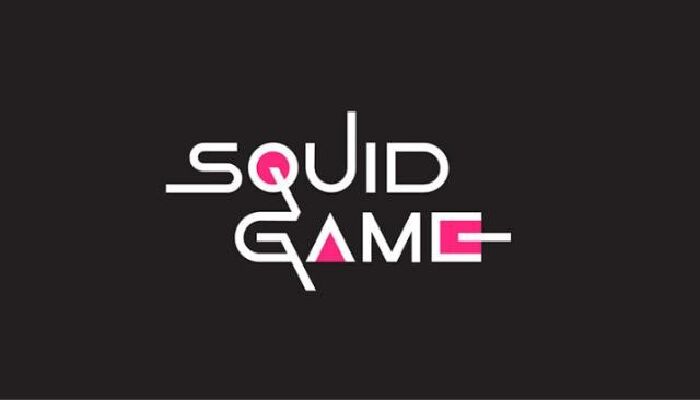
Nếu đã từng coi hoặc biết đến squid game ( trò chơi con mực) thì hẳn là bạn sẽ không còn xa lạ với những kiểu chữ phá cách khác biệt với kiểu chữ truyền thống theo một tiêu chuẩn
Những chữ cái thuộc kiểu Fonts with a Twist vô cùng đa dạng, những chữ cái có thể bị ngược, đảo lộn, kích thước lớn hoặc nhỏ, thậm chí có thể thêm vài ký tự độc đáo để tạo điểm nhấn trong mắt người xem.